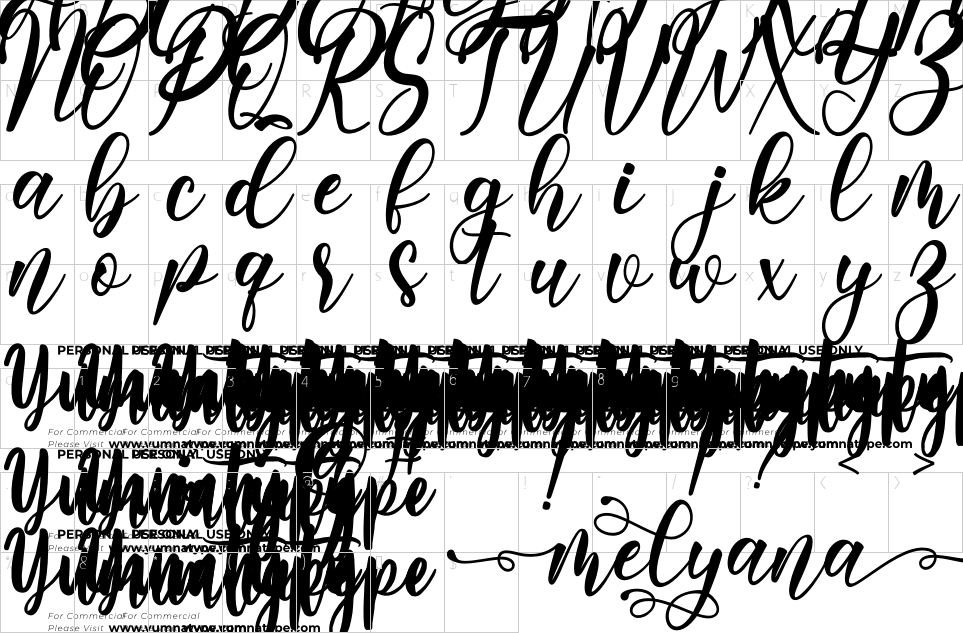
A Melyana Font é uma elegante e sofisticada fonte que está disponível de graça tanto para Windows quanto para Mac. Desenvolvida pela Yumna Type, a Melyana é uma escolha inteligente para qualquer designer ou entusiasta do design gráfico que busca uma fonte minimalista e moderna. Com seu design cuidadosamente criado, a Melyana destaca-se por sua facilidade de leitura e sua versatilidade, adaptando-se perfeitamente a diversos projetos e estilos. Sua simplicidade e elegância não apenas a torna uma opção sólida para textos de destaque, mas também uma ótima opção para textos de fundo e títulos. Com a Melyana, você pode adicionar um toque diferenciado a seus projetos, tornando-os um pouco mais únicos e personalizados. A fonte já foi baixada 1.933 vezes, o que prova seu valor e popularidade. Se você está em busca de uma fonte única e versátil, a Melyana Font é um investimento que vale a pena.